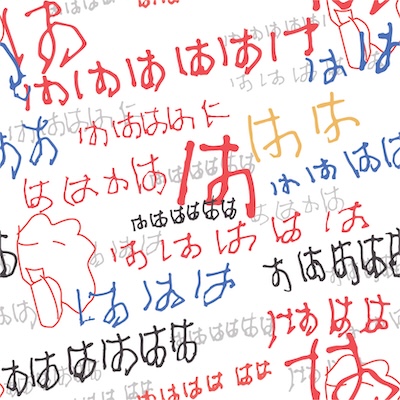
hahahaha
この頃、外で声を出す事が減り、喜怒哀楽の表現の場が曖昧になってきていました。アーティストは自分の世界に決して揺るがない喜怒哀楽があって、作品の表現を通じることで共有ができます。その図案化。素材を通じて、作品を通じて笑う。視覚を通じて、笑いを分かち合う。日常の中ささやかに、あるいは盛大に、はははは、と。(小林 大真)